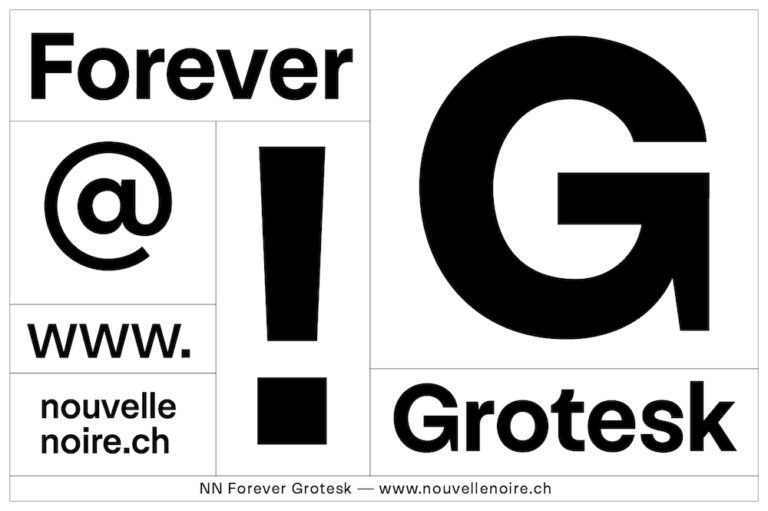
Serifenlose Forever Grotesk: Schweizer Präzisionsarbeit
Brauchen wir eine neue Helvetica? »Ja«, sagt Anton Studer und gestaltete die Schriftfamilie NN Forever Grotesk.
Anton Studer, der gemeinsam mit Clovis Vallois in Zürich die Foundry Nouvelle Noire betreibt, gestaltete die Forever Grotesk, um die Schweizer Groteskschriften aus ihrer Neutralitätsecke zu holen. Max Miedingers Helvetica war 1950 der erste Schweizer Beitrag zu dem noch recht neuen Genre der Groteskschriften, über die Jahre kamen viele weitere dazu – die Welt hat nach wie vor Appetit auf serifenlose Schriften Schweizer Herkunft. 70 Jahre nach der Helvetica will nun auch Nouvelle Noire etwas beitragen und entwickelte die NN Forever Grotesk. »Es hat eine Weile gedauert, die perfekte Form zu finden, die die Lücke zwischen Einfachheit und Neutralität füllt,« so der Typedesigner Anton Studer. »Wir wollten auf keinen Fall eine weitere neutrale Schrift kreieren.«
Statt dessen suchten sie nach Formen, die einfach, aber ein bisschen besonders sind, beim Blick etwa auf das t wird der Ansatz klar. Sieben Strichstärken von Thin bis Fat plus Kursive geben Gestaltern auf jeden Fall genug Möglichkeiten an die Hand, erstaunliche Dinge zu schaffen. Der Name Forever Grotesk kommuniziert den Wunsch von Nouvelle Noire, den Geist der ursprünglichen Groteskschriften zu bewahren.
Mit ihren 14 Schnitten bietet NN Forever Grotesk viele Gestaltungsmöglichkeiten.
NN Forever Grotesk steht zwar in der Tradition Schweizer Groteskschriften, ist aber alles andere als neutral.